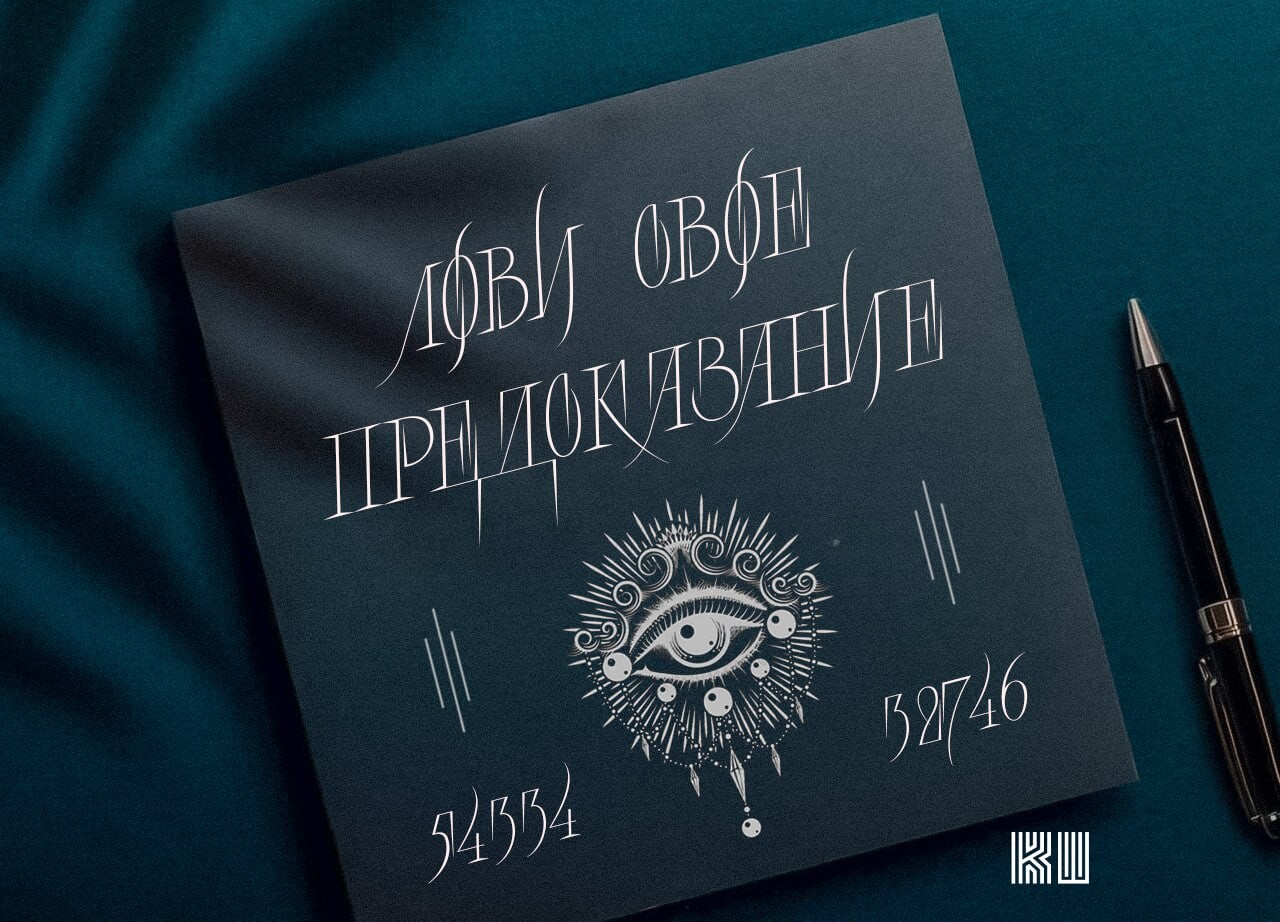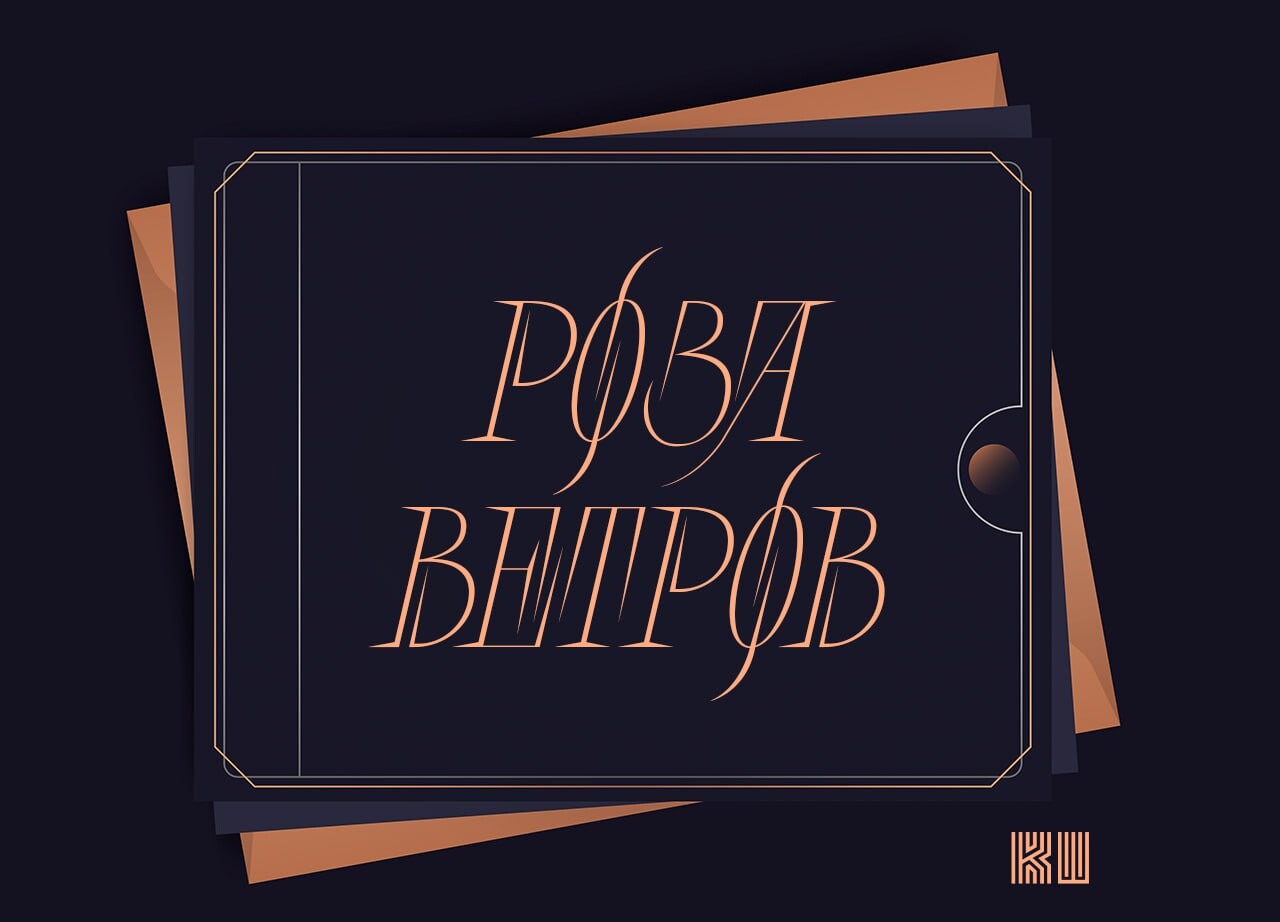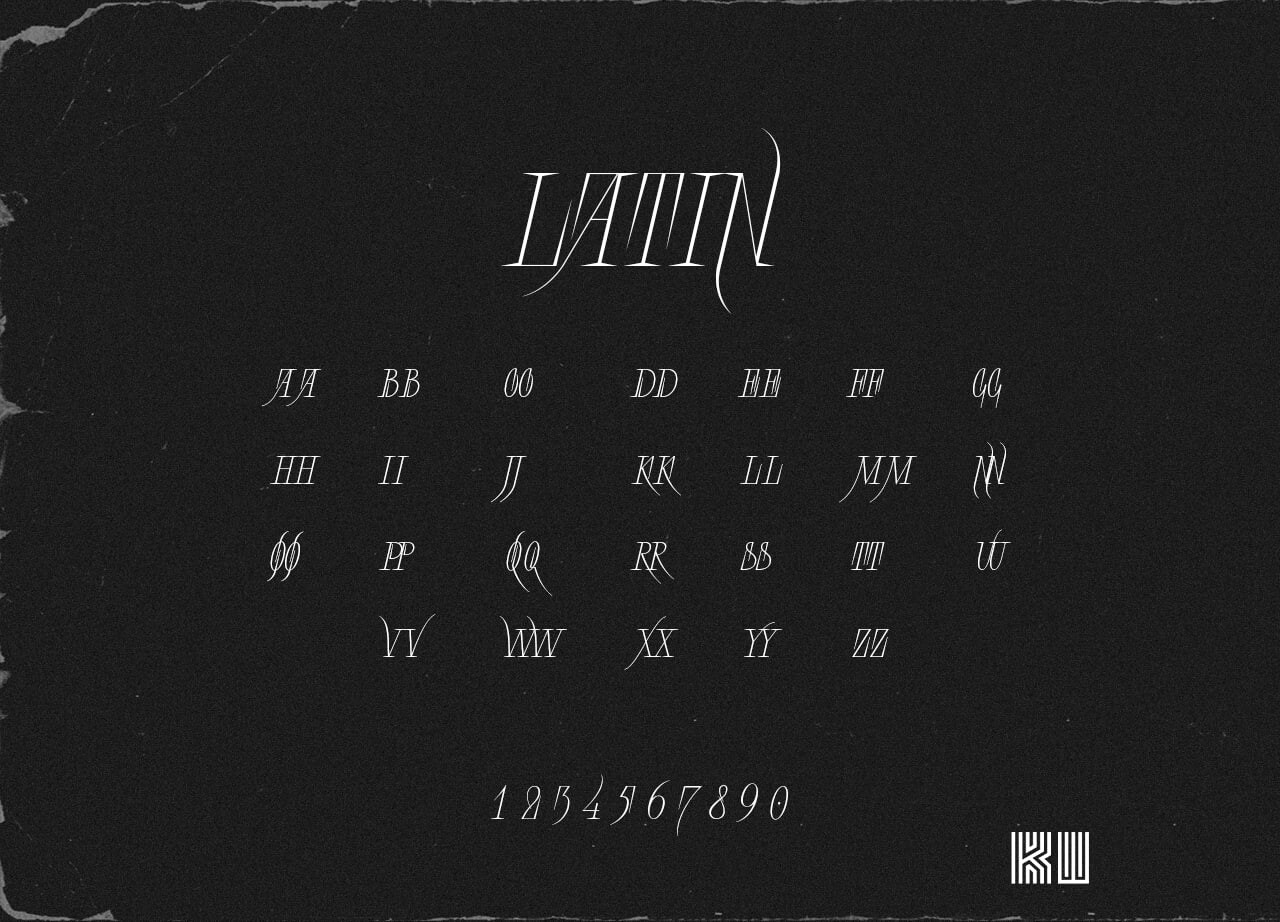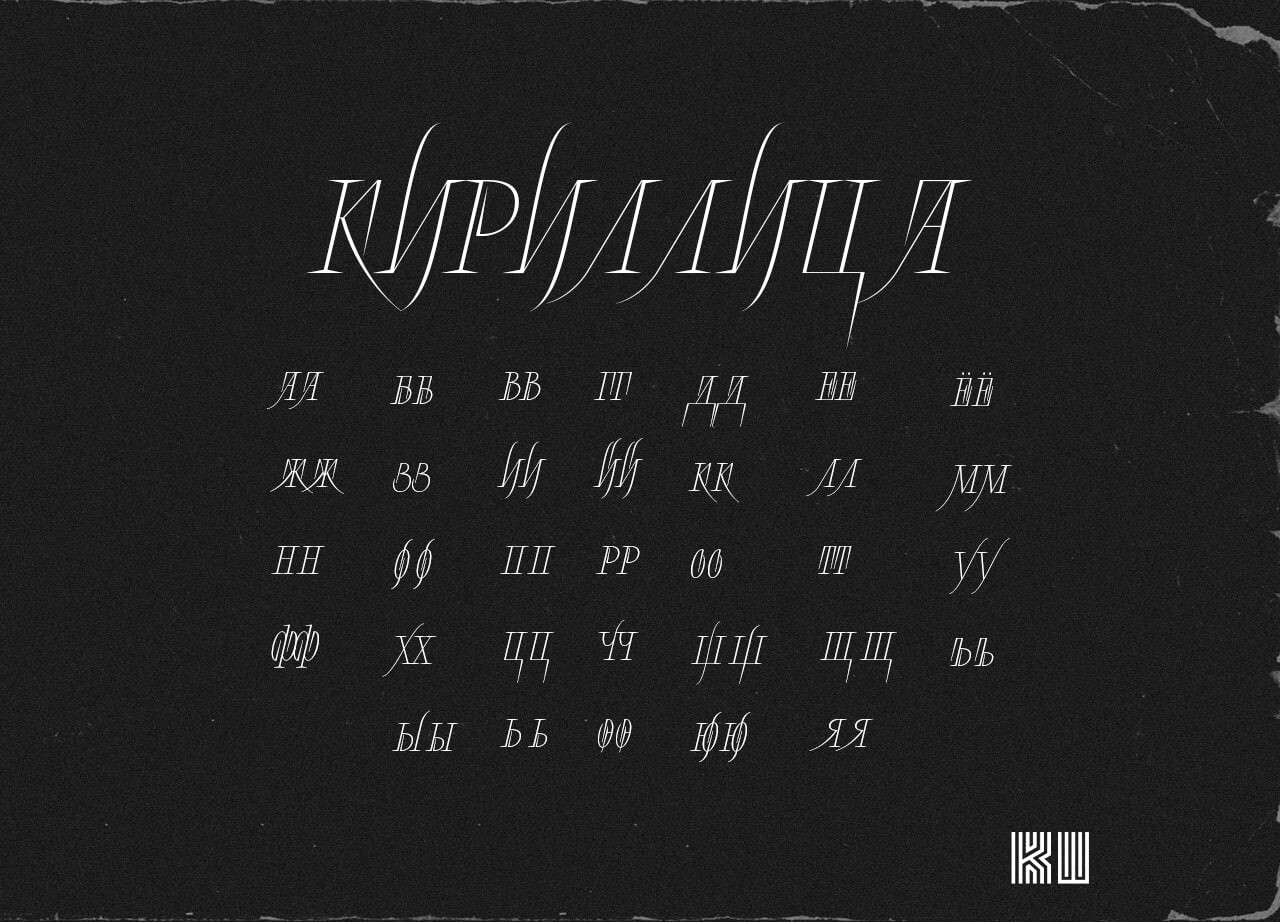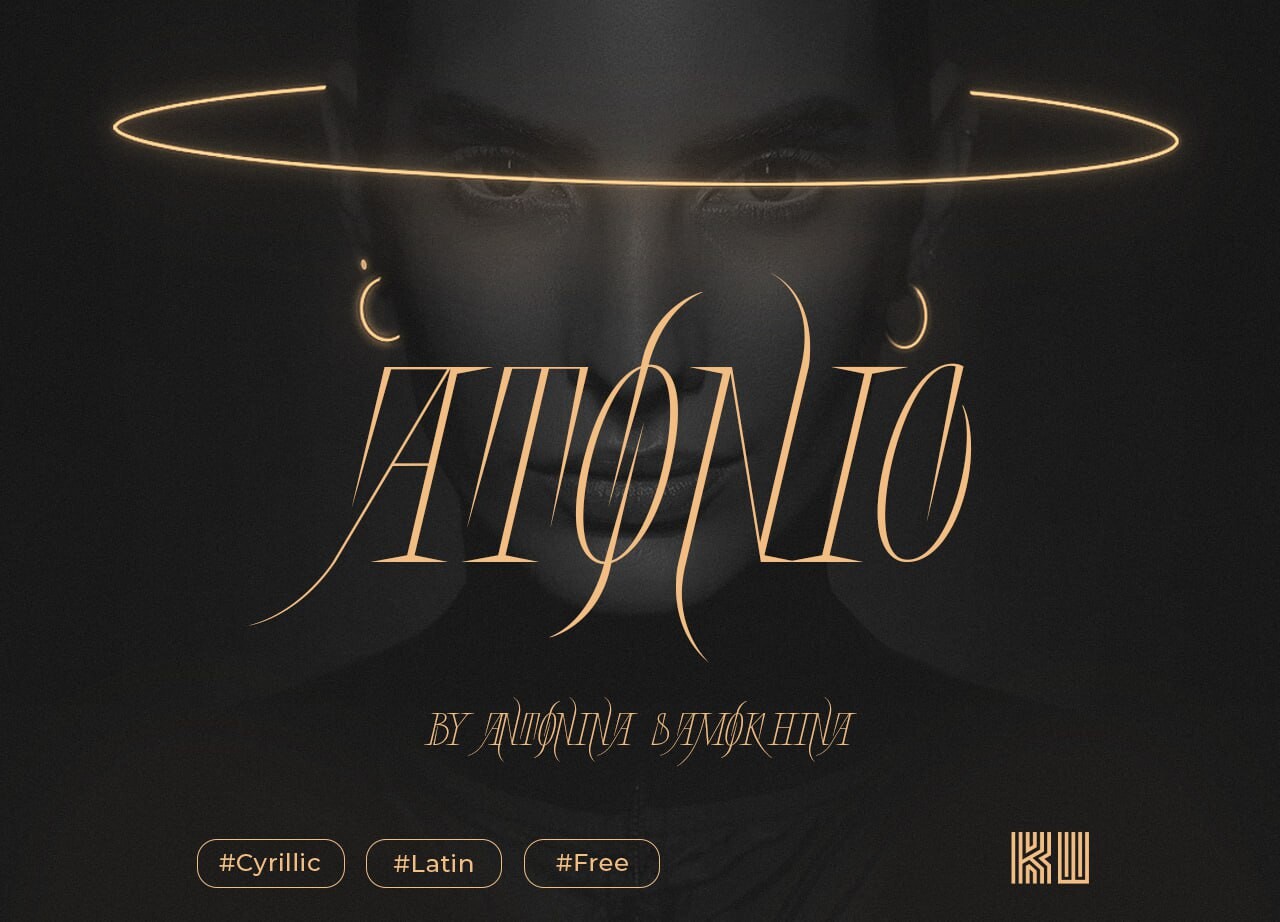
Atonic: дисплейный шрифт с изящными изгибами и острыми шипами 📝
Вы когда-нибудь замечали, как рука сама рисует в воздухе плавные дуги - и вдруг резко останавливается на остром угле? Именно из этого противоречия родился Atonic. Шрифт, который не просто стоит на странице, а будто дышит: то мягко скользит, то вдруг вонзается в глаз. И да, это его главное обаяние.
Что делает Atonic особенным
Он соединяет изящные изгибы естественных движений руки с острыми шипами. Наклон здесь не декоративный каприз - он придаёт символам характер и динамику. Буквы будто слегка наклоняются вперёд, будто готовы сорваться с места. В результате получается не статичная надпись, а живая, почти телесная форма. Смотришь - и кажется, что шрифт вот-вот сделает шаг.
Первый выход "в свет"
Автор шрифта - Антонина Самохина. И вот что она сама говорит о своём дебюте:
"Я впервые вижу свои шрифты „в деле“, и я, несомненно, очень рада. Можно сказать, что это мой шрифтовой дебют, мне приятно, что он состоялся в таком издании как Собака. Удивительное ощущение, когда берёшь журнал в магазине, листаешь его и видишь плоды своего труда. С точки зрения шрифтового дизайна это любопытно вдвойне: видеть, как другой дизайнер использует то, что ты сделал, чтобы выразить уже собственные идеи. Так можно иначе взглянуть на свою же работу и начать привыкать к тому, что разработка шрифта невозможна без мысли о том, как и кто его может использовать. То есть, когда заканчиваешь работу над буквами, веселье только начинается".
Вот оно - настоящее удовольствие дизайнера: отпустить своё создание в чужие руки и увидеть, как оно начинает жить новой жизнью.
Иногда самые интересные вещи появляются именно на стыке мягкости и остроты. Atonic - как раз из таких. Он не просит разрешения быть собой. Он просто есть: живой, чуть колючий и неожиданно грациозный. И когда его буквы появляются на странице журнала или в макете, понимаешь - вот оно, настоящее "веселье только начинается".